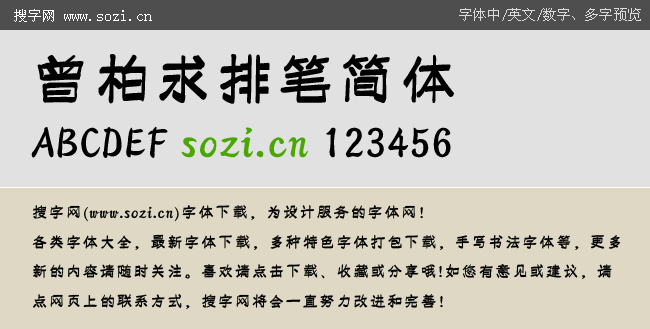
方正字跡-曾柏求排筆簡體
搜字網(wǎng)給大家提供一款方正字跡-曾柏求排筆簡體中文字體下載。方正字跡-曾柏求排筆簡體綜合了楷、隸、黑體的特點(diǎn),獨(dú)具一格,用筆方圓結(jié)合,在規(guī)范書寫方式的前提下,融入了更多圓潤流暢、時尚柔美的設(shè)計(jì)元素。此款字體適用于包裝設(shè)計(jì)、廣告設(shè)計(jì)、海報設(shè)計(jì)等視覺環(huán)境。